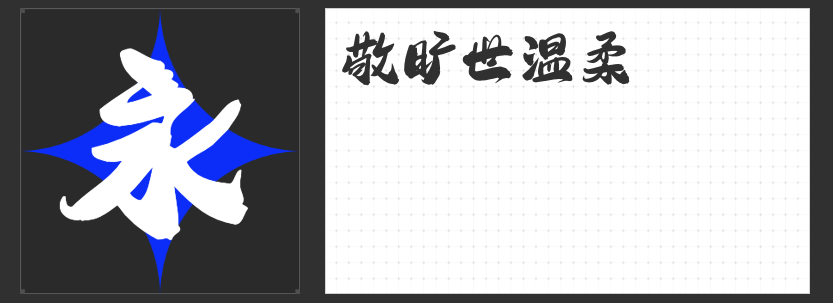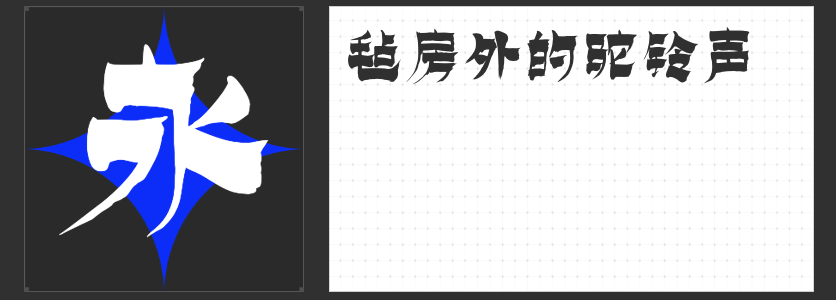
国潮新风尚:四款不可错过的创意字体推荐
在国潮文化日益兴盛的今天,字体设计作为视觉传达的重要组成部分,正以其独特的魅力吸引着越来越多人的目光。今天,就为大家推荐四款极具特色的国潮字体,它们不仅各具特色,更在各自的领域内展现出了非凡的创意与表现力。
这款字体以其笔墨浓厚、粗细对比鲜明的特点脱颖而出。字体结构中正,笔画中的“勾、提、挑、捺”等细节被夸张处理,极具视觉冲击力。单字结构收放自如,仿佛每一笔都蕴含着无穷的力量,是展现力量与美感并存的绝佳选择。
作为一款创意十足的毛笔手书字体,永刚漆书以其厚重的笔画和清晰的撇字赢得了广泛赞誉。字体框架醒目,字型端庄,风格统一,无论是包装印刷还是广告设计,都能轻松驾驭,展现出独特的艺术魅力。
3.造字侠侠道简繁
字形饱满而松弛自然,回锋收笔间透露出一种从容不迫的气质。转折处的笔画突出,适度的夸张和飞白处理,赋予了字体一种立于天地间的桀骜不驯之感。整体布白均匀,风格独特,节奏鲜明,是追求个性与自由的创意人士的不二之选。
4.高手兵克逍遥体
这款字体以其独特的韵味和流畅性赢得了众多设计师的喜爱。笔画间既有传统书法的韵味,又不失现代设计的简洁明快。无论是用于品牌标识还是海报设计,都能轻松营造出一种逍遥自在、无拘无束的氛围。
四款字体,四种风格,它们共同构成了国潮字体设计的璀璨星空。无论你是设计师还是字体爱好者,都能在这里找到属于自己的那份独特与魅力。让我们一起,用文字的力量,书写国潮新风尚!